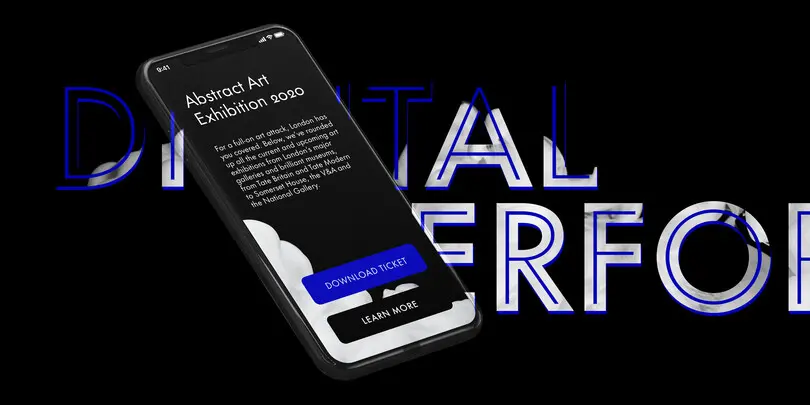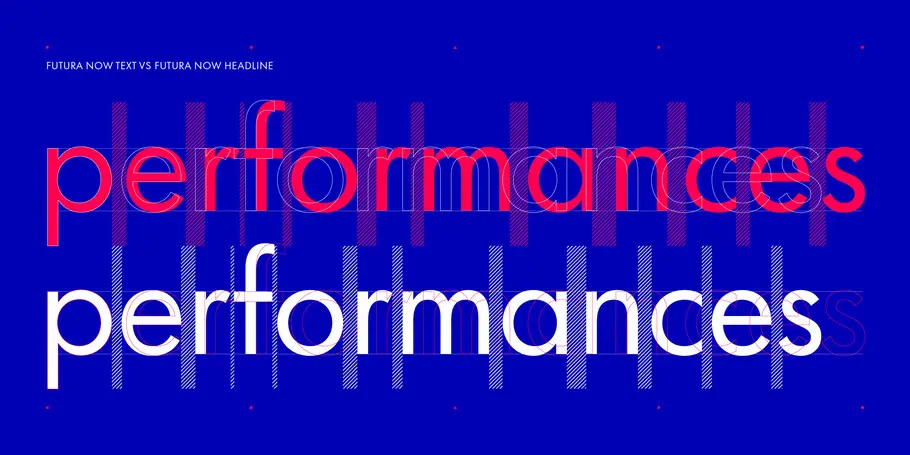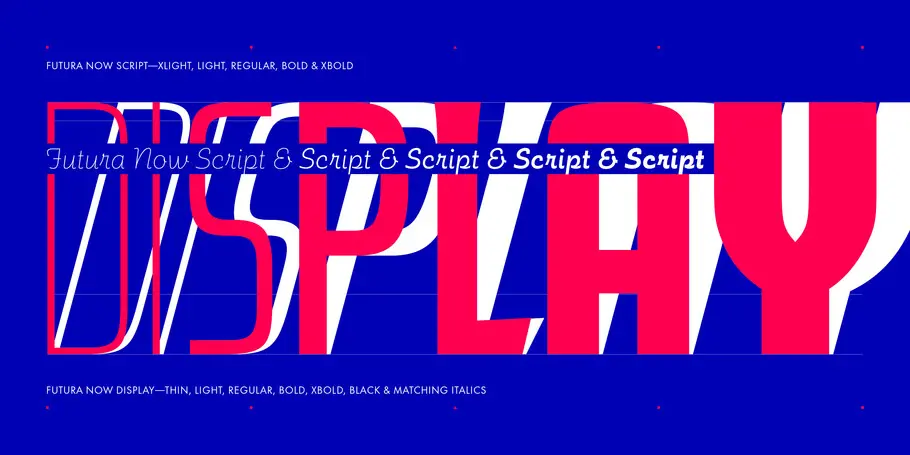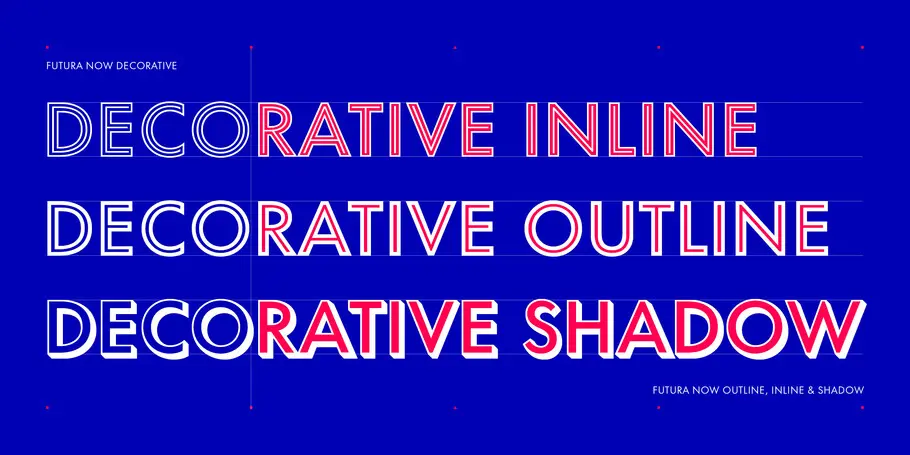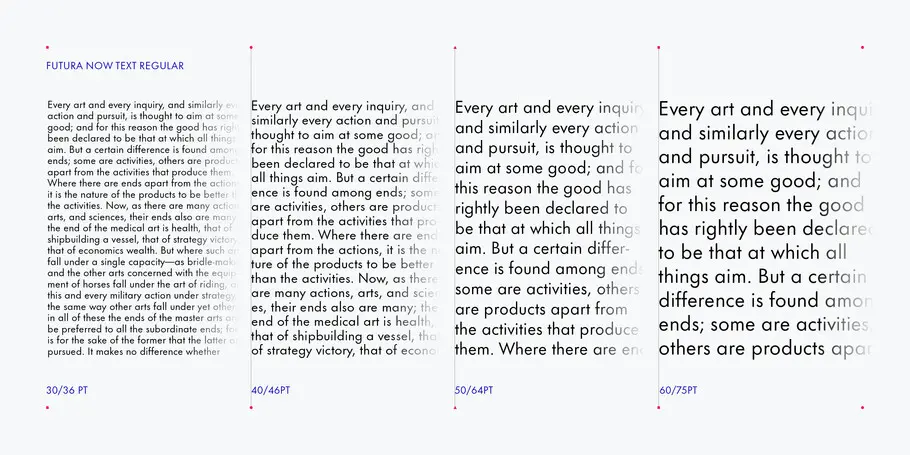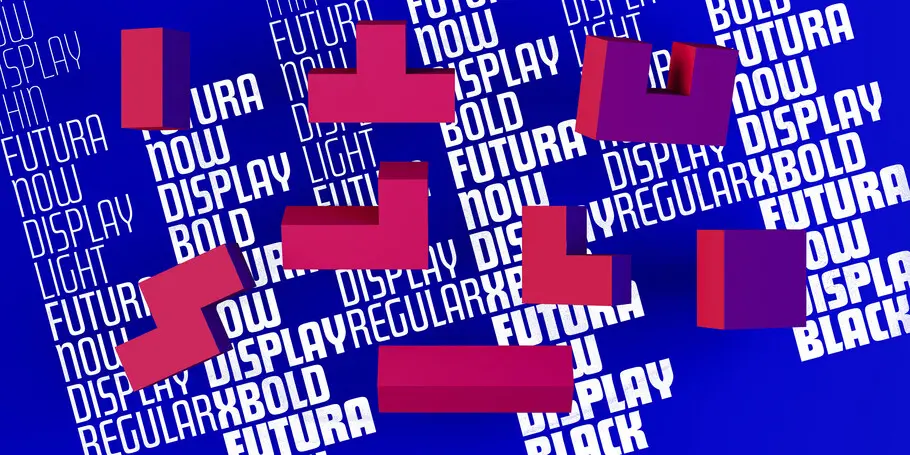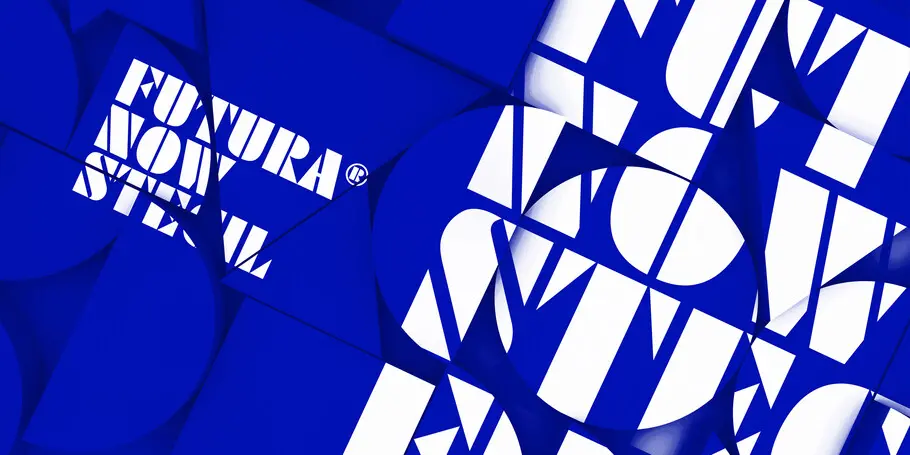
Futura en el próximo siglo.
« Nos preguntamos: ¿cómo debería ser esta familia en la actualidad? ¿Cuál sería la mejor versión de Futura para los próximos cincuenta o cien años? Y eso es lo que nos propusimos crear. »
Juan Villanueva, diseñador tipográfico.
Resulta difícil imaginarse el siglo XX sin Futura. La fuente Futura, de Paul Renner, lanzada por la fundición tipográfica Bauersche Gießerei en 1927, fue un éxito casi instantáneo que adquirió rápidamente el estatus de icono y que ha dejado una huella imborrable en la cultura popular.
Futura es una fuente atemporal en el sentido más estricto de la palabra. Se trata de una tipografía tan camaleónica que, en palabras de Steve Matteson, director creativo de tipografía de Monotype, «encaja igual de bien al lado de una secuoya que de una mesa de acero».
Pero el siglo XX ya es cosa del pasado. La era dominada por la imprenta en la que prosperó Futura ha dado paso a décadas de avances digitales para los que no está preparada. Irónicamente, Futura (adaptable, austera y cargada de nostalgia) sigue siendo tan popular e indispensable como antaño y es, en muchos sentidos, el contrapeso estético perfecto para una cultura obsesionada por la tecnología.
Dicho esto, ¿cómo debería ser la Futura del siglo XXI? Debería estar optimizada para la lectura en pantallas OLED brillantes y de alta resolución, así como en las diminutas pantallas de los relojes inteligentes. Debería ofrecer pesos cuidadosamente diseñados para cada uso y reflejar una nueva estrategia de espaciado. Debería incorporar una fuente variable que proporcionara la máxima flexibilidad y la posibilidad de ajustar los diseños al detalle. Y debería representar toda la historia de Futura en una sola versión, incluidas las ramificaciones extravagantes, como los estilos Script y Display.
Debería ser justamente todo lo que es Futura Now.
Sin necesidad de ajustes adicionales.
«Lo más importante de Futura Now es que es fácil de usar tal y como está», afirma Terrance Weinzierl, que formó parte del equipo de Futura Now. Según explica Weinzierl, esto puede parecer una nimiedad, pero utilizar las versiones anteriores de Futura podía «resultar complejo». El espaciado incoherente, la gama limitada de pesos, las oblicuas distorsionadas y la compatibilidad con pocos idiomas limitan la capacidad de Futura para satisfacer las necesidades de las marcas modernas y digitales. «Si, por ejemplo, nos fijamos en el diseño de Linotype de Futura, vemos que es un poco estrafalario», comenta Weinzierl. «Hay que utilizarlo con prudencia».
« Lo más importante de Futura Now es que es fácil de usar tal y como está. »
Terrance Weinzierl, diseñador tipográfico sénior.
La clave de la facilidad de uso de Futura Now son los tamaños ópticos del tipo de letra: Futura Now Text y Futura Now Headline. Aunque en algunos casos los tamaños ópticos se crean redibujando las formas de las letras para optimizar la legibilidad en determinados tamaños y distancias de lectura, el tamaño óptico de Futura Now se centra únicamente en los problemas de espaciado mencionados.
Como su propio nombre indica, Futura Now Text presenta un espaciado amplio para optimizar la lectura de textos extensos. Las formas de letras clásicas de Futura tienen un poco más de espacio para «respirar» en la página y, sobre todo, en la pantalla. Esto se nota especialmente en los pesos más estrechos, que ofrecen un espaciado añadido gracias al que los trazos finos destacan. Futura Now Headline reduce un poco ese espaciado, tanto para ahorrar espacio en configuraciones de texto más limitadas, como para lograr el impacto visual que ha hecho de Futura la fuente favorita de publicistas y artistas.
«El espaciado es una parte muy importante del diseño», afirma Juan Villanueva, diseñador tipográfico de Monotype que también trabajó en el desarrollo de Futura Now. «Añadir un poco de espaciado adicional nos permite obtener un tipo de letra mucho más legible en diferentes tamaños».
Estos ajustes ya se notan en los materiales impresos, pero donde realmente dejan huella es en los diseños digitales. «La calidad de la pantalla está alcanzando a la del papel», afirma Weinzierl. «En 1995, las pantallas eran tan rudimentarias que los tamaños ópticos no se habrían podido leer. Ahora, llevamos pantallas de 400 ppp en la muñeca. Tenemos muchos más píxeles con los que trabajar». Los tamaños ópticos aprovechan al máximo esos píxeles y ofrecen una legibilidad prístina en prácticamente cualquier entorno digital.
« El espaciado es una parte muy importante del diseño. Añadir un poco de espaciado adicional nos permite obtener un tipo de letra mucho más legible en diferentes tamaños. »
Juan Villanueva, diseñador tipográfico de Monotype.
Futura Now también incluye las primeras versiones de fuentes variables de Futura, disponibles en las subfamilias Text y Headline (que están combinadas), Display y Script. Las fuentes variables a veces se desarrollan por separado o como acompañamiento de fuentes existentes; pero Futura Now «nació ya como fuente variable», apunta Weinzierl, que afirma que las fuentes variables se desarrollaron desde el principio para que fuesen exactamente iguales a las versiones estáticas.
Las fuentes variables ofrecen un número casi infinito de posibilidades, pero Monotype Studio incorporó lo que Wienzierl y Villanueva llaman «marcadores» que se ajustan a los pesos estáticos como una presintonía en la radio. Esto significa que los equipos de diseño pueden ajustar Futura Now hasta grados infinitesimales, pero volver rápida y fácilmente al peso requerido por la marca al seleccionar el nombre de estilo en el menú de fuentes, como harían habitualmente.
«Lo que hemos hecho es analizar, limpiar y ordenar todo el universo Futura para que quienes usan la tipografía hoy en día puedan entenderla», explica Villanueva. «Nos preguntamos: ¿cómo debería ser esta familia en la actualidad? ¿Cuál sería la mejor versión de Futura para los próximos cincuenta o cien años? Y eso es lo que nos propusimos crear».